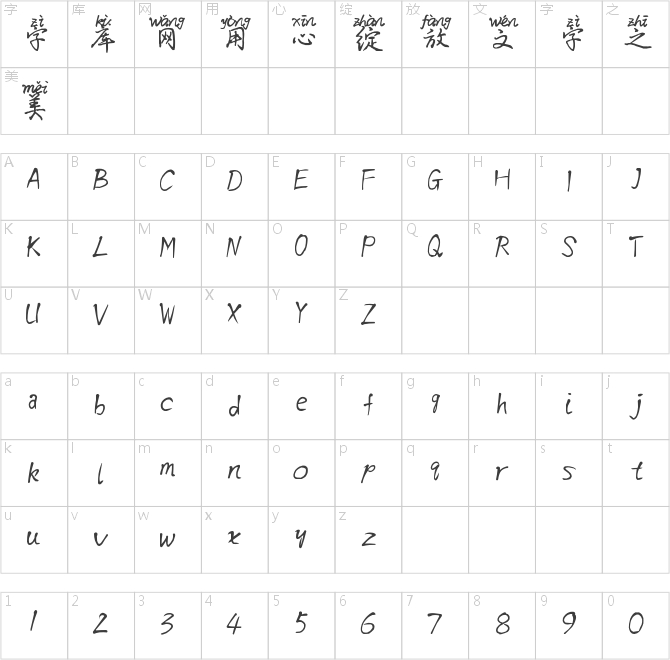
字體名稱: 未署名情書拼音
未署名情書拼音體
該字體行筆自然,轉角圓潤,從容不迫,結構嚴謹不呆板,起收筆間體現良好的書法功底。適用于文藝類的書刊、品牌廣告和產品包裝設計,以及社交網絡的個性化用字。
未署名情書拼音體字體FZSJ-WISMQSPYT字庫是一款讓人賞心悅目、百看不厭的中文字體,適合各類廣告和產品包裝設計應用,字體大小10.56MB,格式為TTF字體,上傳用戶是伍佰,作者/版權方為方正手跡